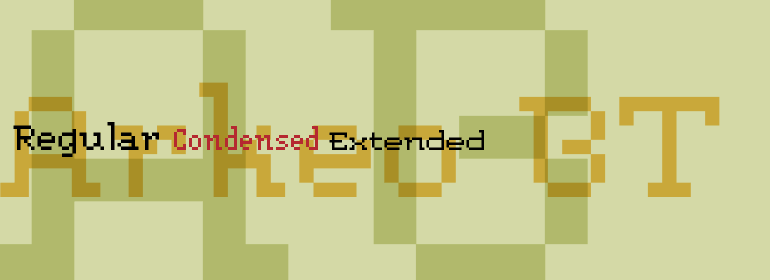
Arkeo BT
Arkeo BT,这款字体结构工整、笔画清晰,兼顾美观与易读性,适用于标题、正文、海报、包装、LOGO 等多种场景。字形优雅稳定,风格百搭耐看,适配日常排版与创意设计,让文字呈现更舒适、更具质感。Arkeo BT一笔一画,皆是细节,以均衡的比例、流畅的线条打造舒适视觉体验,字形端正大气,风格简约现代。无论是商业设计、品牌宣传还是日常排版,都能轻松驾驭,让文字更有格调与力量。Arkeo BT字体下载。